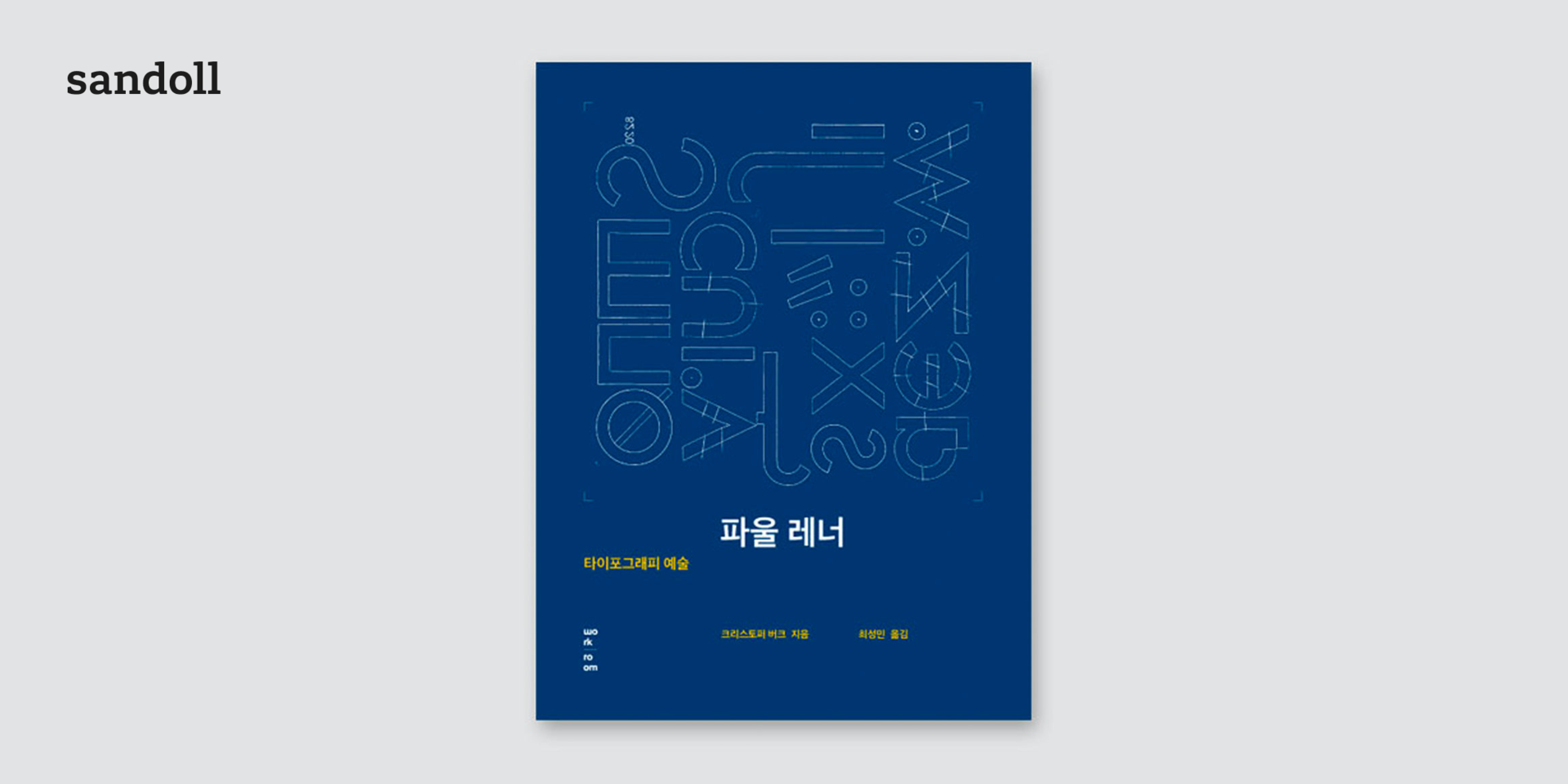
Sandoll 고딕Neo1
산돌 고딕Neo1는 다양한 웨이트의 슈퍼 패밀리를 갖춘 프리미엄 고딕 폰트이다.산돌의 기술과 경험을 집약한 프리미엄 본문서체 Sandoll Neo Series의 일환으로서 기존 산돌 고딕의 고전적인 모습에서 현대적인 세련됨이 돋보이도록 디자인하였다.사용자 중심의 설계로 사용성과 가독성을 최우선으로 고려하였으며 기본적인 네모꼴에 글자와 여백을 가지런하게 안배하여 안정적인 느낌을 부여했다.